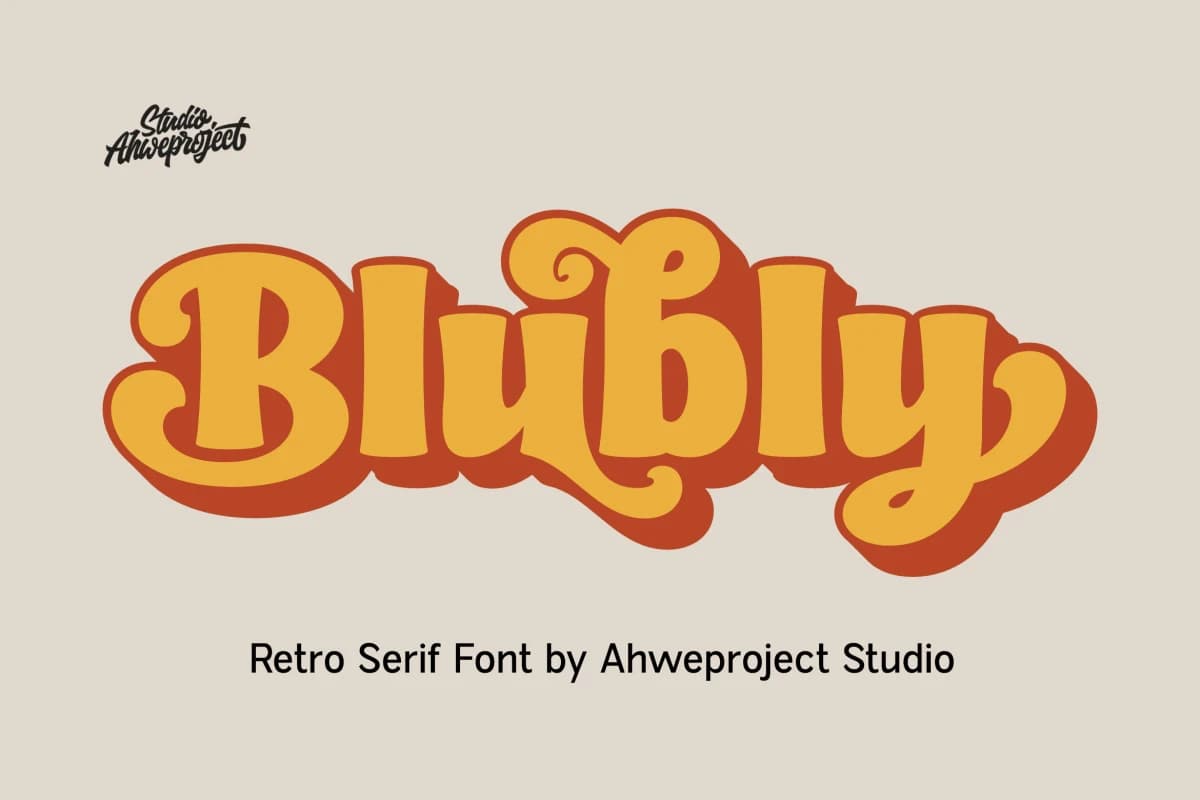
Bluby Font
Bluby Font, vintage tabelalardan, havalı estetikten ve altın çağın nostaljik tipografisinden ilham alan cesur, retro bir serif yazı tipidir.
Bluby Font, vintage tabelalardan, havalı estetikten ve altın çağın nostaljik tipografisinden ilham alan cesur, retro bir serif yazı tipidir. Kalın harf biçimleri, eğlenceli kıvrımları ve göz alıcı stiliyle Bluby, her türlü yaratıcı projeye sıcaklık, kişilik ve zamansız bir çekicilik katıyor.
Posterler, marka oluşturma, ambalaj, logolar, ürünler, kafe tasarımları, müzik kapakları, sosyal medya grafikleri ve retro temalı projeler için mükemmel olan bu yazı tipi, eğlenceli ve samimi bir havayı korurken anında güçlü bir görsel etki yaratıyor.
Bluby, ister otantik vintage havası ister modern retro tasarımlar yaratmak isteyin, tipografinizi öne çıkaran özenle hazırlanmış karakterlerle birlikte gelir.